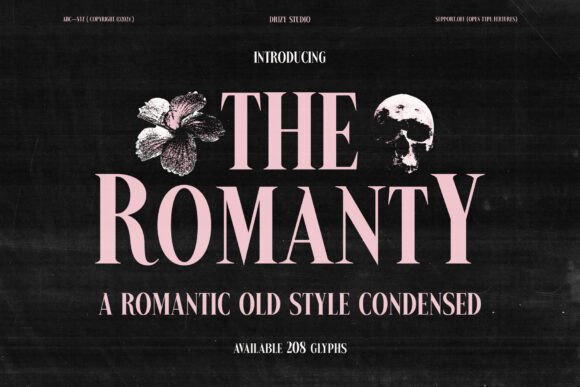
The Romanty
إذا كنت تبحث عن أصول عالية الجودة مثل The Romanty، فإن هذه الحزمة المميزة هي خيار رائع لمشاريعك الإبداعية.
تم تصميمه بدقة، ويوفر The Romanty متجهات نظيفة وطباعة سلسة وترخيصًا تجاريًا لراحة بالك.
سواء كنت تقوم بإنشاء منتجات الطباعة عند الطلب أو دعوات الزفاف أو رسومات وسائل التواصل الاجتماعي، فإن The Romanty هو الخيار المثالي.